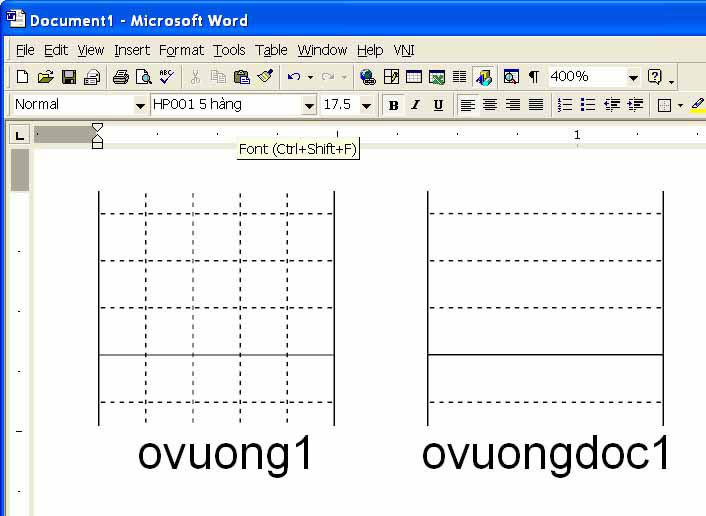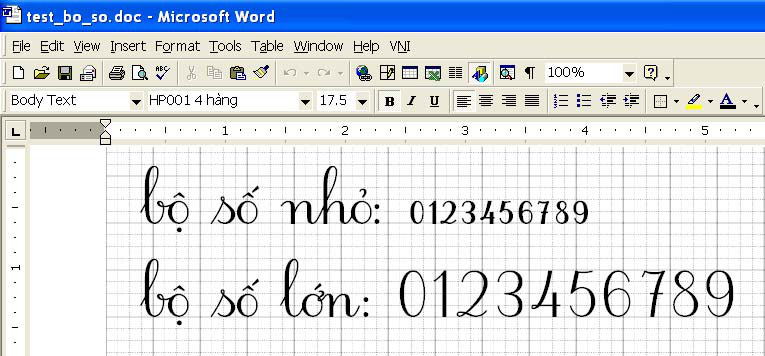
Mẫu Font Chữ Tập Viết Tiểu Học
VnDoc.com xin gửi tới bạn đọc bài viết mẫu font chữ tập viết tiểu học để bạn đọc cùng tham khảo. Mẫu font chữ tập viết tiểu học với những mẫu font chữ chuẩn và đẹp theo HP001 (2.0) để thầy cô cho các em học sinh luyện viết hàng ngày. Mời thầy cô cùng tham khảo chi tiết và tải về mẫu font chữ tập viết tiểu học tại đây.
Mẫu font chữ tập viết tiểu học
Hướng dẫn sử dụng HP001 (2.0)
2- Soạn thảo một văn bản tiếng Việt bằng mã Unicode để tạo ra tài liệu mình cần. Sau đó truy cập vào link Chuyển mã trên web site http://tapviet.tk, dán văn bản đó vào khung soạn thảo (dùng chức năng copy/past), bấm vào nút chuyển mã chương trình sẽ thực hiện chuyển mã. Tiếp theo là copy đoạn mã trả về và dán trở lại chương trình đang sử dụng, là hoàn tất.
3- Phông HP001 có 2 loại: 4 hàng và 5 hàng. Loại 4 hàng thì giống tập học sinh 4 ô ly, nhưng không thể hiện được các ký tự Ô Ắ ... Tất cả có 4 file phông bao gồm:
1- HP001 4 hàng bold
2- HP001 4 hàng normal
5- HP001 5 hàng bold
6- HP001 5 hàng normal
Nếu các bạn muốn hiển thị ô vuông giống như tập học sinh thì làm như sau:
- Trong lúc chuyển mã các bạn đánh thêm vào một từ ovuong1 hoặc ovuongdoc1. Trong quá trình chuyển mã chương sẽ trả về hình của một ô vuông. (các từ ovuong2, ovuong3 sẽ cho đường kẻ dày lên tương ứng, xem hình).
Copy ra cho đủ số hàng mà bạn cần. Sau đó tạo một cái textbox, rồi dán đoạn văn bản đã chuyển mã vào đó, điều chỉnh cho textbox ngay hàng với những ô li bên dưới là hoàn tất.
Chú ý: Phải chọn kiểu phông cho ovuong1 và textbox giống nhau. Size trong textbox gấp đôi size ovuong1 sẽ cho chữ 2 ô ly, còn bằng nhau là 1 ô ly.
Nếu không cần những ô vuông có đường kẻ dọc thì bạn dùng những phông có sẵn ô ly.
4- In ấn:
- Để in ra giống tập học sinh 4 ô ly các bạn size phông ovuong1 là 17.5 point
- Phần văn bản trong textbox các bạn chọn:
17.5 point tương đương 1 ô ly
35 point tương đương 2 ô ly
- Phần máy in các bạn phải chọn độ phân giải là 1200 dpi. Nếu độ phân giải là 600 dpi thì nó không thể hiện được các chi tiết trong ovuong.
5- Một số vấn đề cần lưu ý khi chuyển mã:
- Khi nhập văn bản vào khung soạn thảo, để chương trình chuyển mã làm việc chính xác, càn có các điều kiện sau:
Xuống hàng phải có các dấu: chấm, chấm phẩy, chấm hỏi, chấm than, ba chấm ...
Đầu dòng phải viết hoa
Dấu ngoặc kép phải đúng chiều. Ví dụ: "Đúng" "Sai"
Trường hợp viết ngắt dòng như trong khổ thơ (cuối dòng không có dấu gì), có thể chương trình chuyển mã không đúng. Trong trường hợp này các bạn phải thêm một khoảng trắng ở cuối dòng.
6- Bộ chữ số:
- Bộ chữ số ở lớp một, chiều cao chỉ bằng 1/2 bộ chữ số bình thường, vì vậy để thể hiện nó, khi chuyển mã các bạn nhập thêm phía sau nó một dấu hoa thị:
Ví dụ: 1*2*3*4*5*6*7*8*9*0* (xem hình)
7- Kiểu viết 2: Đối với các ký tự có 2 kiểu viết, các bạn có thể dùng link chuyển mã II để đổi sang kiểu viết 2. Để chuyển mã bộ số đúng bạn hãy chừa 1 ký tự trắng trước nó.
VD: 1 2 3 4 5 6 7 8 9 0 hoặc 1* 2* 3* 4* 5* 6* 7* 8* 9* 0*